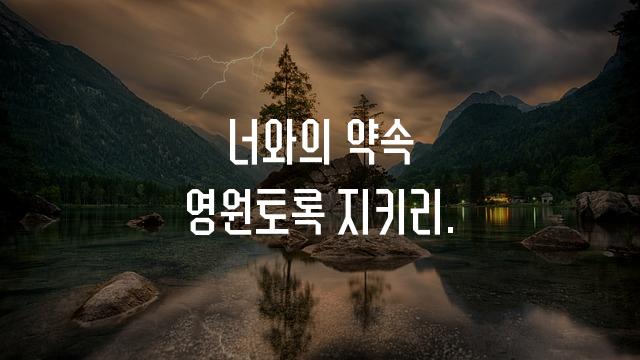
사월십육일체 안전은 4・16재단에서 제작한 독특하고 키가 큰 장식체 폰트입니다. 감성적으로 컬러풀하고 독창적인 디자인이 특징입니다.
사월십육일체 안전은(는)
두꺼운 스타일, 장식 스타일, 색연필, 별모양/패턴, 길고/크고 계열의 생김새를 가지고 있으며
웹/앱 디자인, 프레젠테이션, 보고서/문서 등에서 자주 활용되며, 효과적인 메시지 전달에 적합합니다.
이 폰트는 기술/IT, 헬스/의료, 금융/비즈니스 분야에 잘 어울리며,
명확한, 전문적인, 단순한 느낌을 담고 있는 것이 특징입니다.
이 폰트와 유사한 폰트로는 Helvetica Neue, Roboto, Futura 등이 있어요. 함께 비교해 보시면 좋습니다!